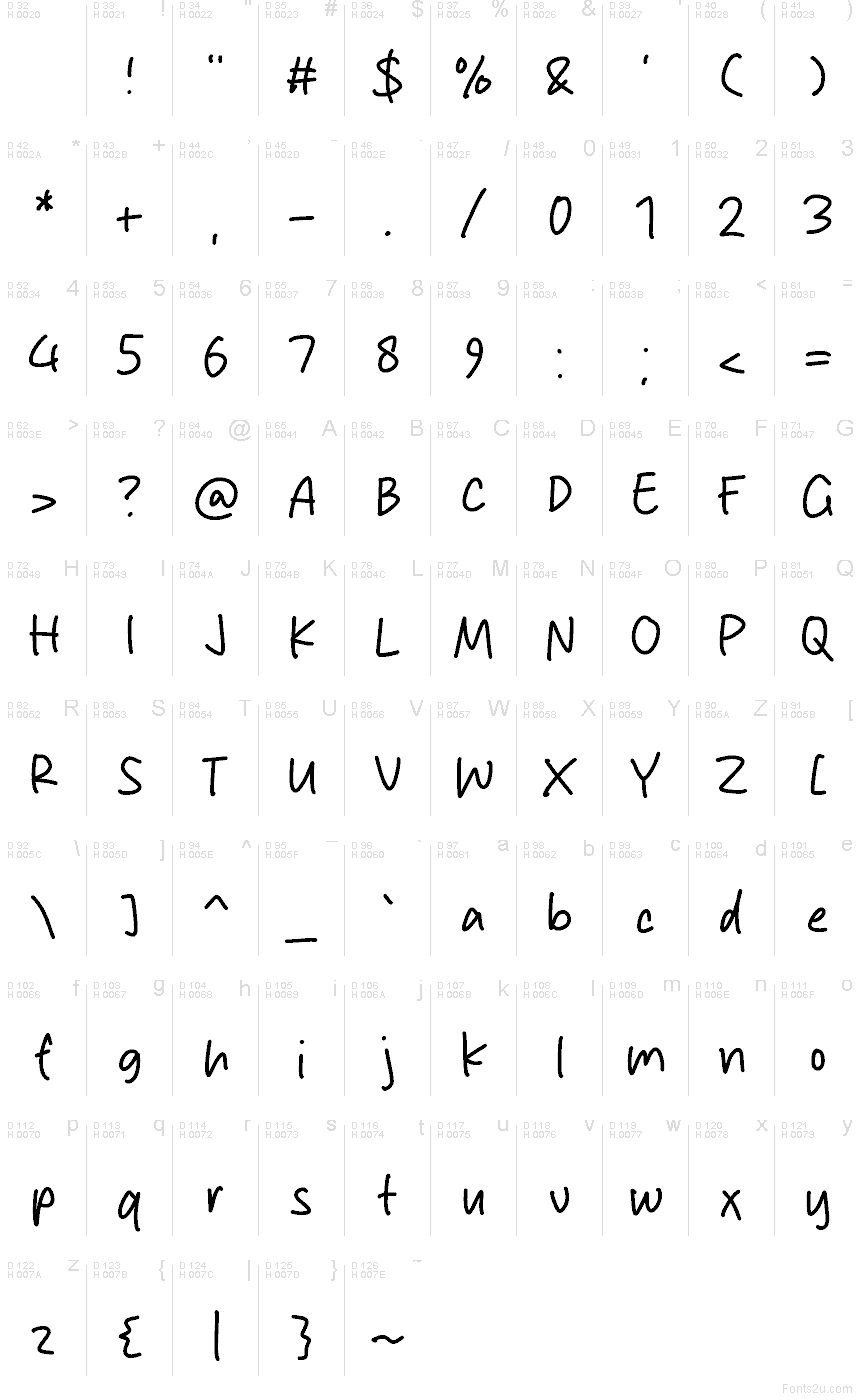
Privilege People da Origin Type é uma fonte manuscrita gratuita com um ritmo descontraído e amigável, e um charme ligeiramente irregular que a torna muito pessoal. As letras parecem desenhadas rapidamente, com pontas arredondadas, traços irregulares e uma leve oscilação entre os caracteres, fazendo com que o conjunto pareça mais um bilhete informal do que uma caligrafia polida.
É perfeita para branding jovem, embalagens informais, gráficos para redes sociais, títulos de cartazes e capas de livros ou zines, onde se pretende que uma fonte gratuita transmita humanidade em vez de perfeição técnica. Use-a para títulos, nomes ou citações curtas quando quiser que aquele toque natural desenhado à mão faça a diferença.